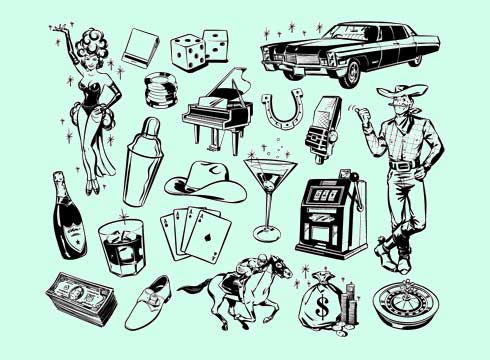
Bis 20. November 2009 feiert FontShop sein 20-jähriges Bestehen, täglich mit einem Lieblingsprodukt, reduziert um 20 Prozent (siehe Fontblog-Ankündigung 20 Jahre FontShop). Heute im Angebot: die Retro-Schriftfamilie Las Vegas. von House Industries. Das sind 4 Fonts plus ein Set von Illustrationen. Wenn wir schon keine Lizenz zum Gelddrucken haben, dann wollen wir wenigstens Drucksachen entwerfen, die nach Geld riechen. Mit den Las-Vegas-Fonts ist das kein Problem. Passend zur Finanzkrise erscheinen sie für wenige Tage zum Dumpingpreis im FontShop. Direkt zur Bestellseite …
Eine Hommage an die Goldenen Zeiten der Beschriftungen und Schilder von Las Vegas. House Industries sagen dazu: »Long before prosaic pylons swallowed the Strip, Las Vegas offered some of the finest examples of mid-century lettering ever created. These legendary edifices of cement, stone, steel and neon were enchanting landmarks of unprecedented inventiveness. With the Las Vegas font collection, House has revived the insight and imagination not seen since that irrecoverable era of commercial design.«